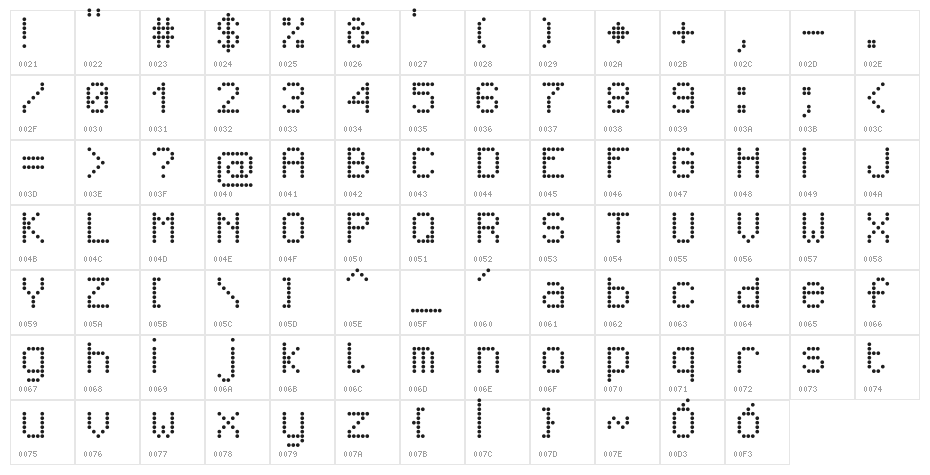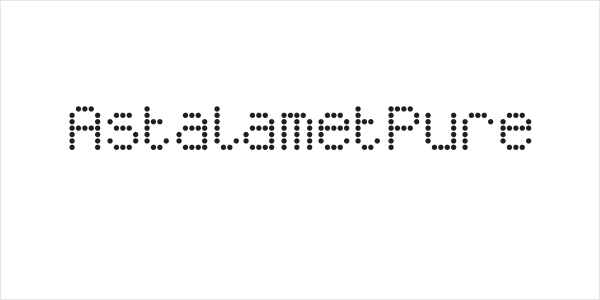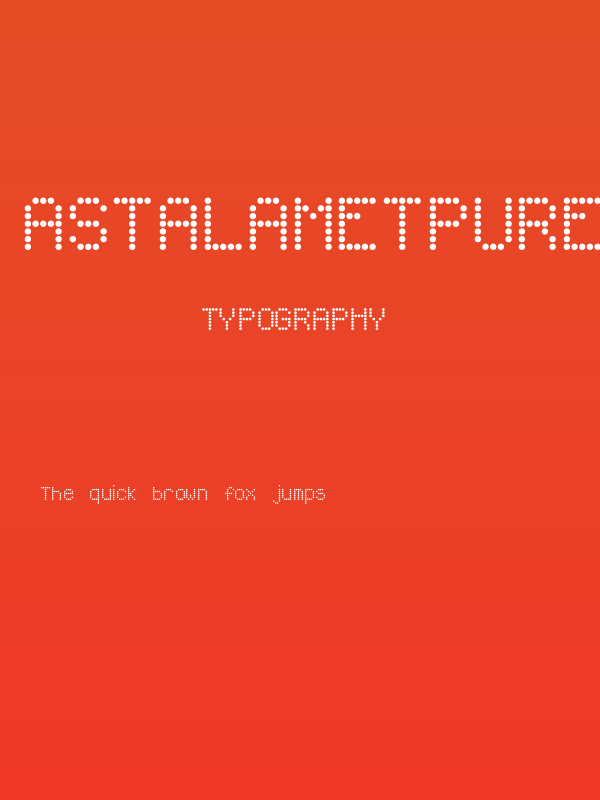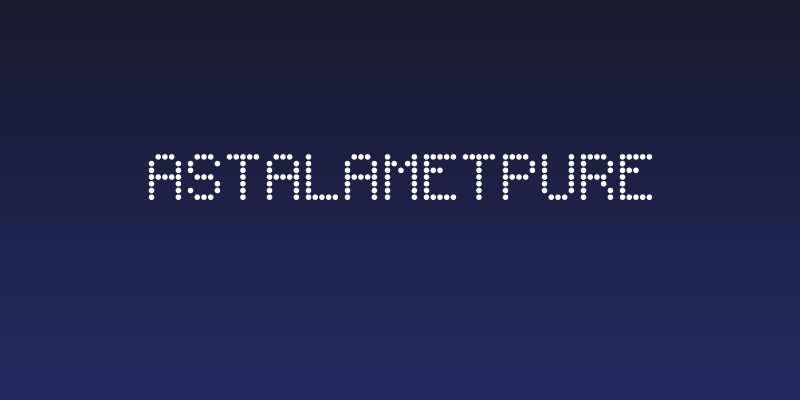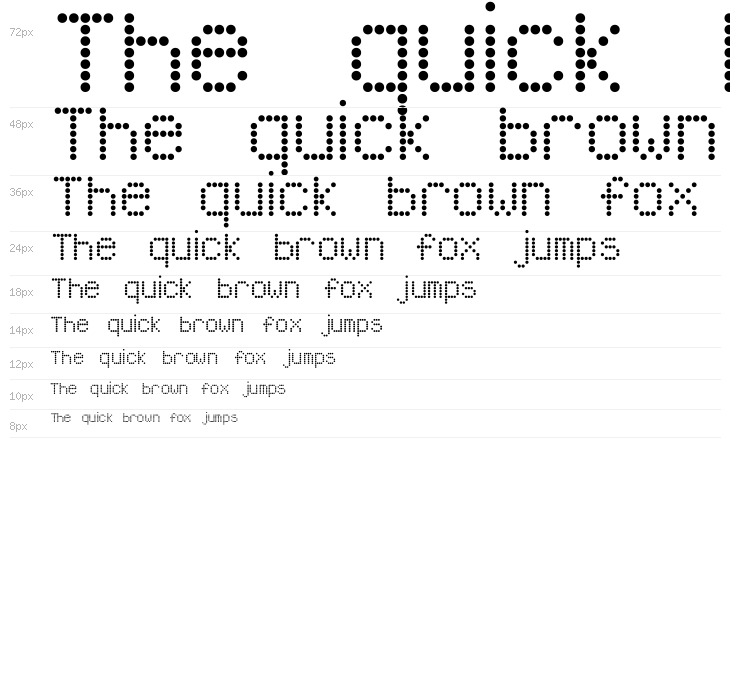
AstalametPure Font
| Caso d'uso | Logos, Headlines, Digital displays |
| Progetti proposti | Ideal for digital art, tech-themed designs, futuristic branding, and innovative product packaging. |